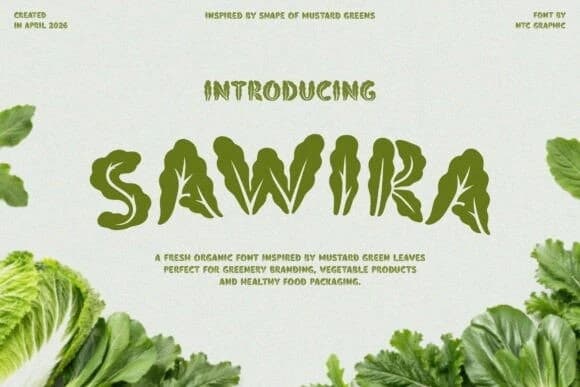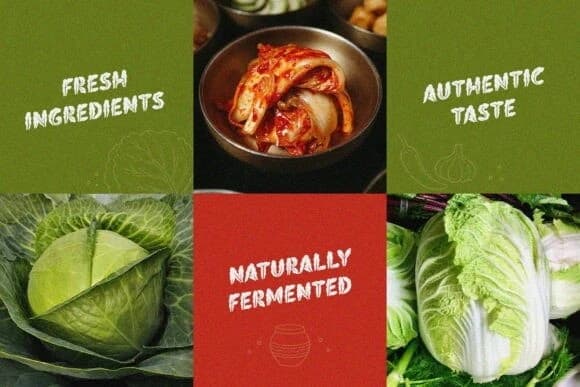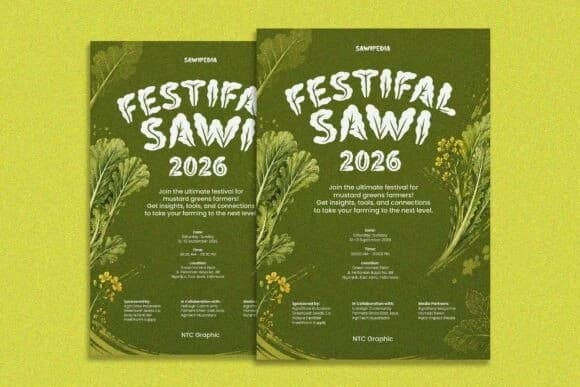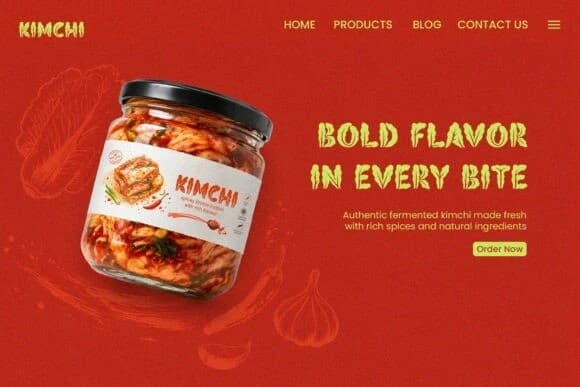
Sawira Display Font
Sawira Display Font, hardal yapraklarının doğal şekillerinden ilham alan benzersiz bir organik gösteri yazı tipidir. Kalın, düzensiz ve yaprak görünümlü harflerle bu yazı tipi tasarımlarınıza taze, doğal ve el yapımı bir his katıyor.
Sawira Display Font, hardal yeşili yapraklarının doğal şekillerinden ilham alan benzersiz bir organik gösterim yazı tipidir. Kalın, düzensiz ve yaprak benzeri harf biçimlerine sahip bu yazı tipi tasarımlarınıza taze, doğal ve el yapımı bir his katıyor.
Sawira Display